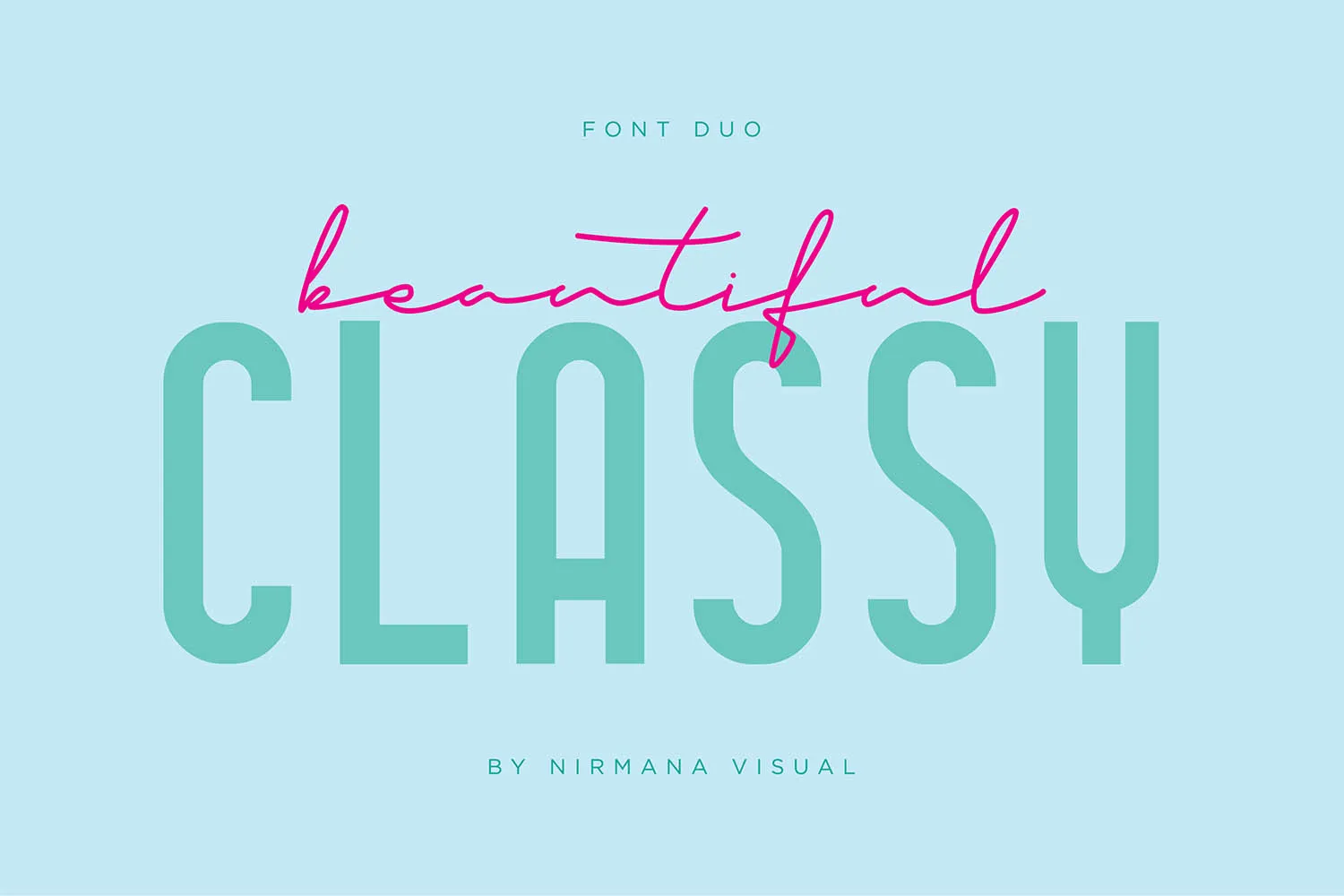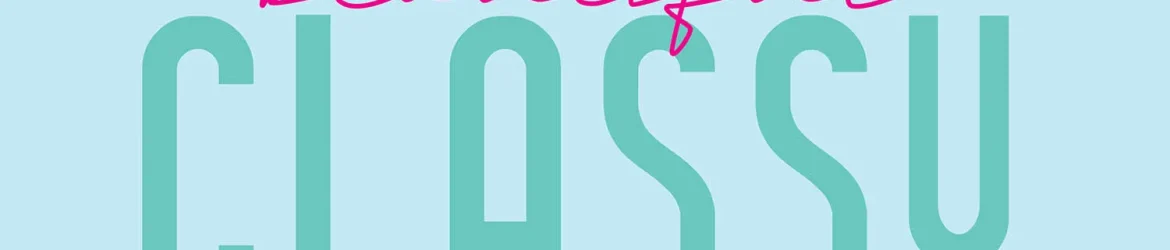
A Classe Estética Duo é uma dupla única e irresistível de tipos que vem para revolucionar seu portfólio de design. Introduzida pela Nirmana Visual, esta fonte Script oferece uma harmonia tipográfica sofisticada e contemporânea perfeita para uma variedade de projetos de design, incluindo logotipos e marca, desenhos para casamentos, postagens nas redes sociais, anúncios e designs de produtos. Suas linhas suaves combinam perfeitamente com o modernismo da fonte sans-serif, criando uma combinação harmônica que certamente brilhará em qualquer trabalho gráfico. Composta por um conjunto de tipos elegantes e versáteis, a Classe Estética Duo é a escolha perfeita para quem busca tanto estilo quanto funcionalidade em suas soluções typográficas.